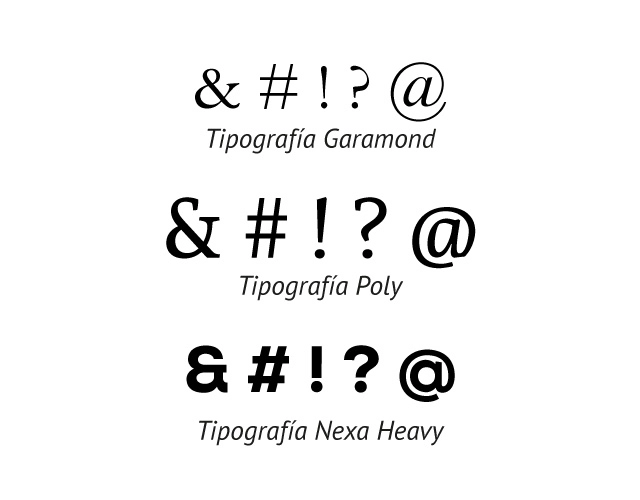
MISCELÁNEA
El término miscelánea hace referencia a aquellos caracteres o signos no alfabéticos que pueden tener formas abstractas o decorativas. Ejemplos de misceláneas son los símbolos, filetes, ornamentos, asteriscos, viñetas, bullets, etc. Suelen ser utilizados para acompañar, resaltar, ilustrar u ordenar la presentación de los textos.
Su origen proviene de los ornamentos y filetes decorativos denominados “Drolleries” de los primeros libros objeto medievales “codex”